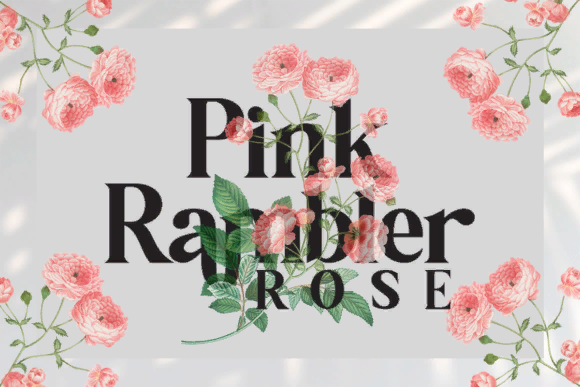
Название: Botanist Font (2021)
Botanist - это современный и элегантный шрифт с засечками.
Смело добавляйте его в свои любимые творения и позвольте себе поразиться полученному результату.